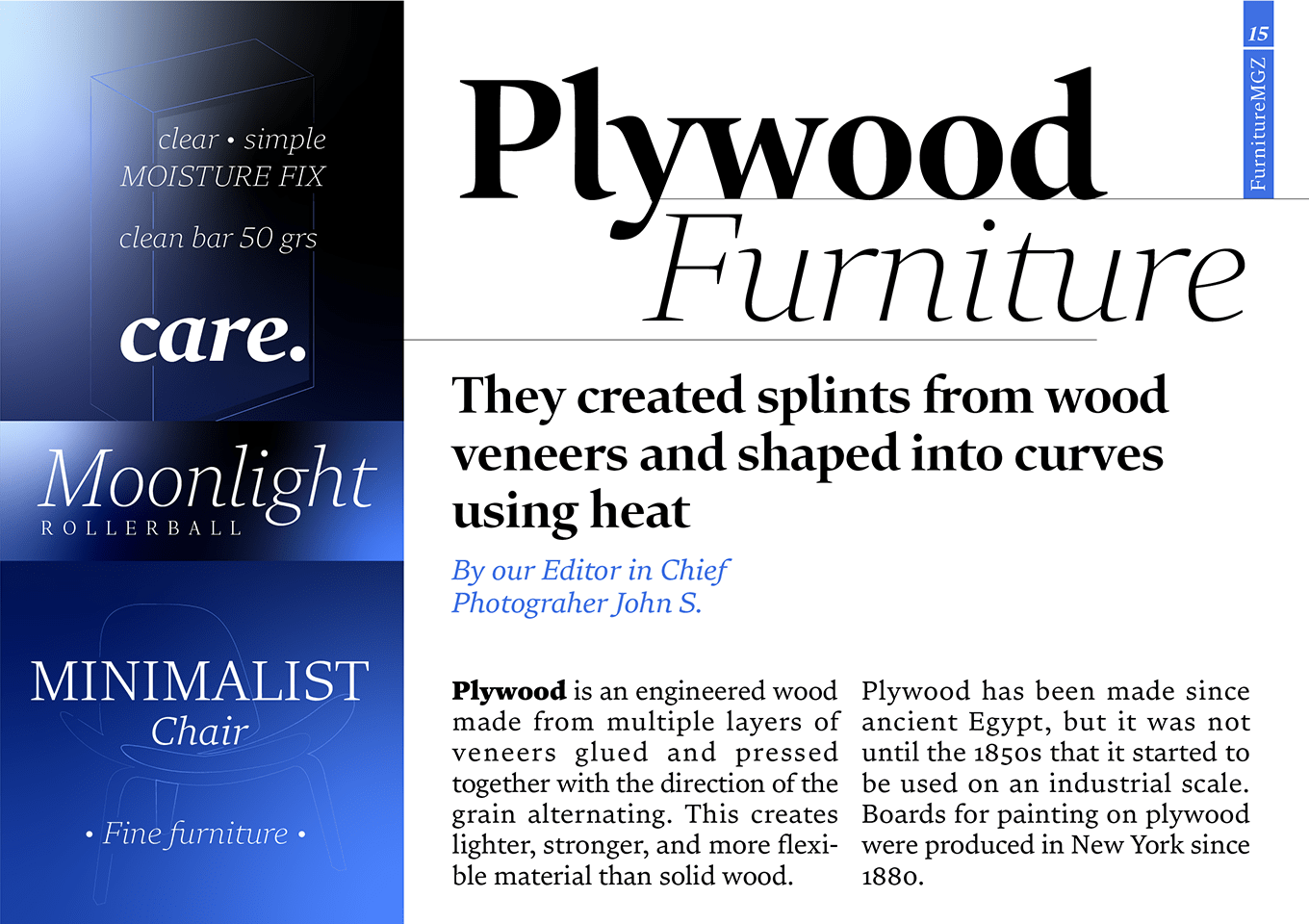
Roleは 、セリフ、サンセリフ、スラブセリフ、ソフト(ラウンデッド)の4つのスタイルと、Text(本文用)、Display(小見出し用)、Banner(大見出し用)の3つのサイズ別に最適化されたバリエーションを持つ、合計200書体のスーパーファミリー書体です。すべての書体は、「誠実さ」と「安定感」をコアイメージとし、Serifは「エレガント」をテーマに制作されています。 Role Serif Textは堅牢かつ高い可読性を持つ本文用書体です。